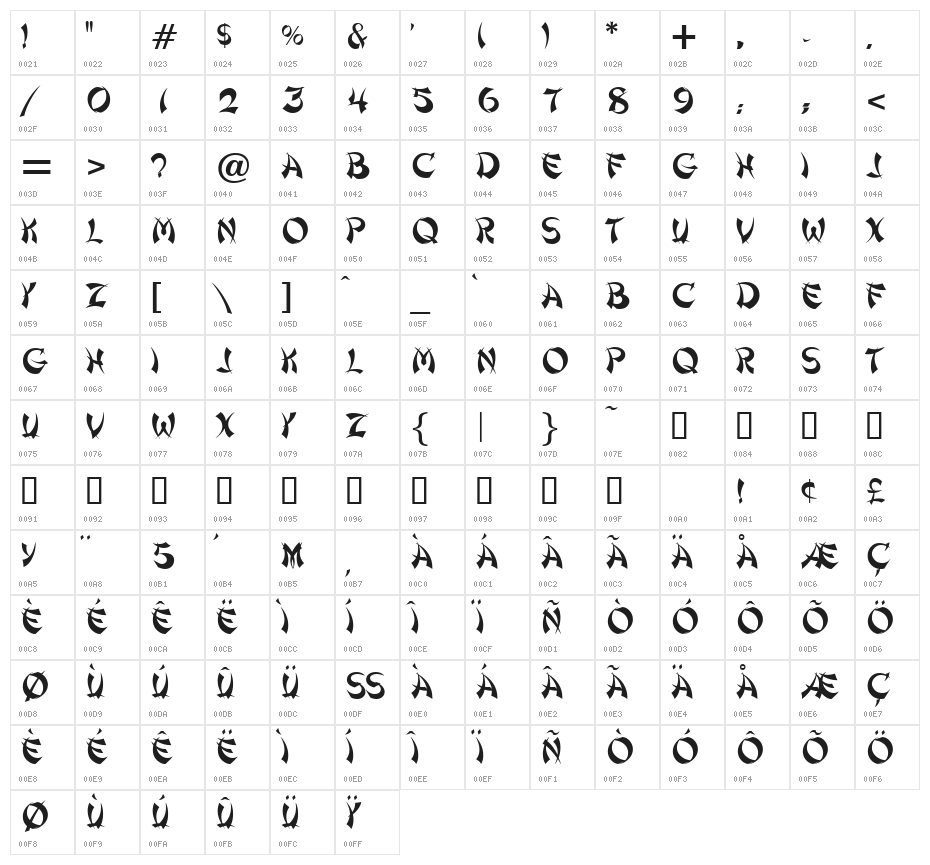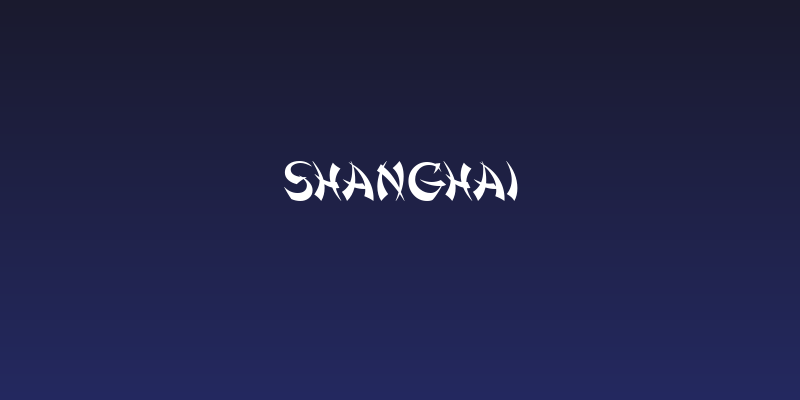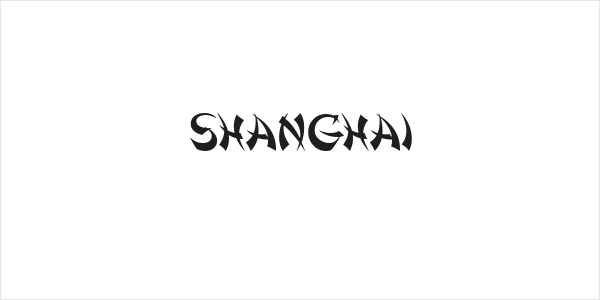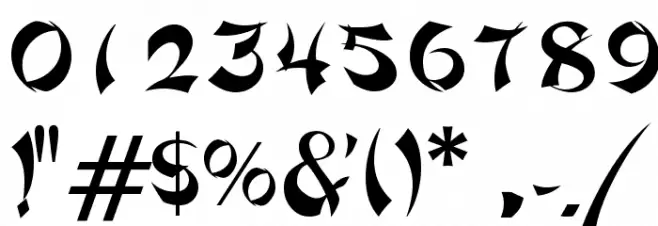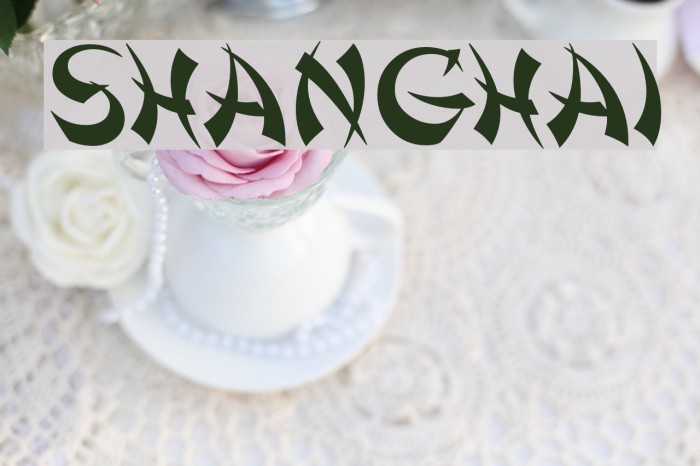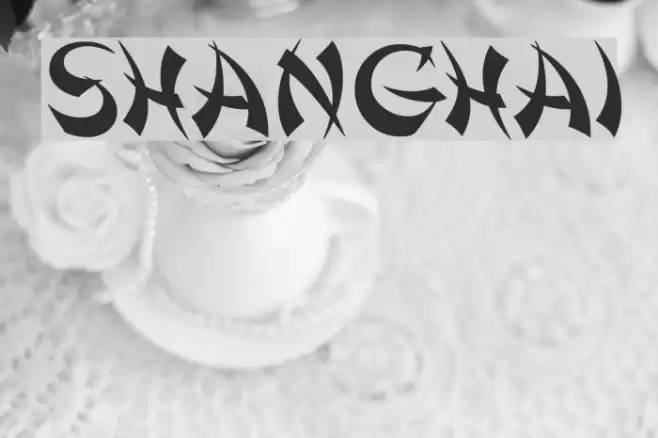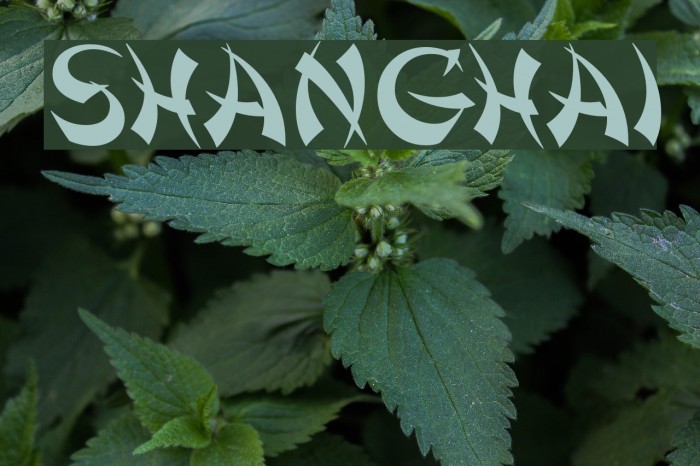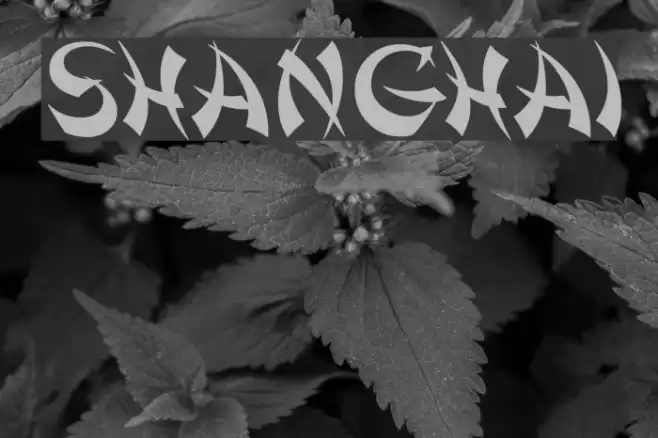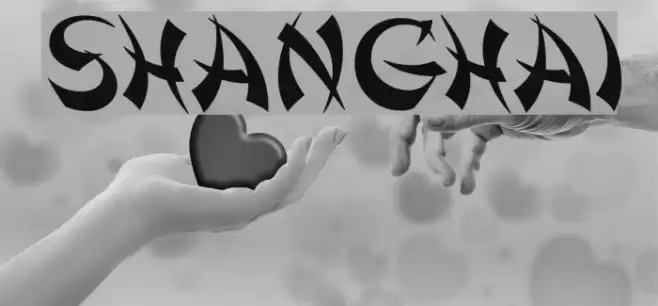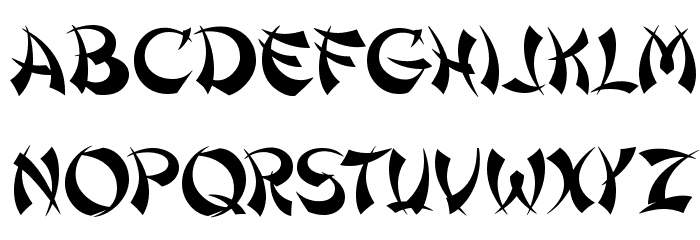
Shanghai Font
يتضمن هذا الخط 187 حرفًا. انقر على أي حرف لرؤية التفاصيل.
| النمط العام | Gothic, Dramatic |
| مشاريع مقترحة | Ideal for album covers, posters, branding for edgy or alternative products, and any design requiring a bold statement. |